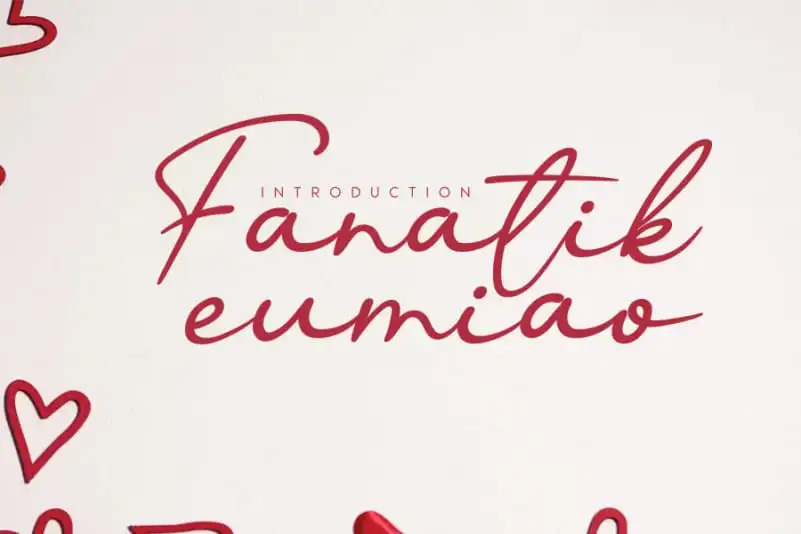
Fanatik Handwritten Font – Download Grátis
A Fanatik Handwritten Font é uma delícia para os olhos. A sensação geral é de conforto e charme, com suas linhas suaves e detalhes cuidadosamente criados que se assemelham a uma carta escrita à mão. Seja para um convite de casamento requintado, cartões de agradecimento, mensagens poéticas ou até mesmo para logos e cards empresariais, a Fanatik Handwritten Font oferece uma aparência estonteante e elegante. Essa fonte transmite conforto e delicadeza, tornando-a perfeita para projetos que precisam de um toque autêntico e pessoal. Sempre em sua forma graciosa, ela se adapta a diversos tipos de projetos gráficos, mantendo sempre a beleza da escrita à mão. Engane-se ao pensar nela como apenas uma fonte; com seu design cuidadosamente elaborado, a Fanatik Handwritten Font realmente se revela o tipo de recurso que vai tornar suas criações únicas e memoráveis.